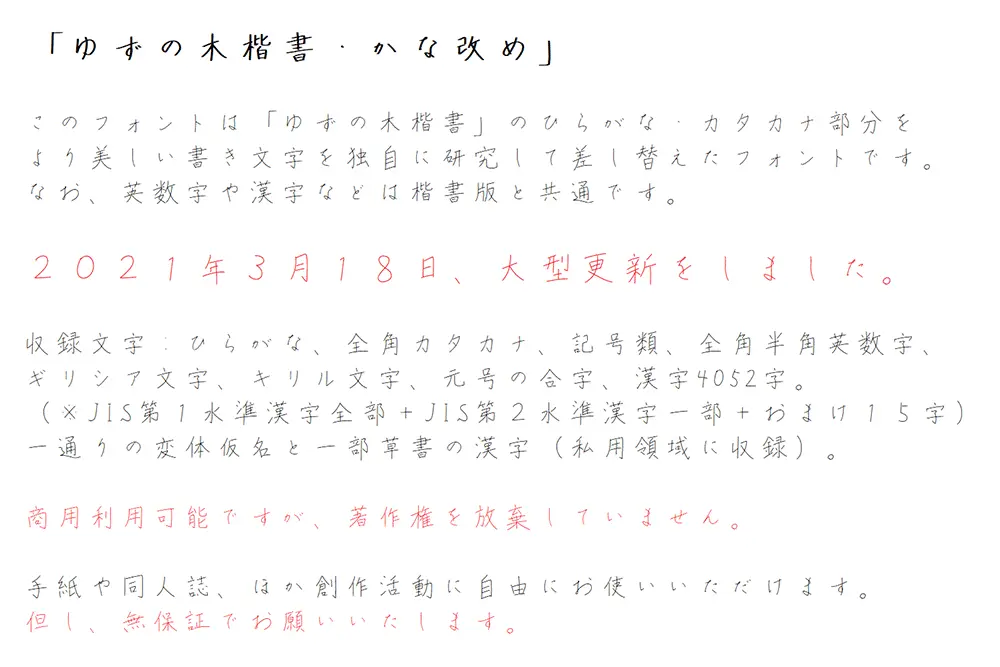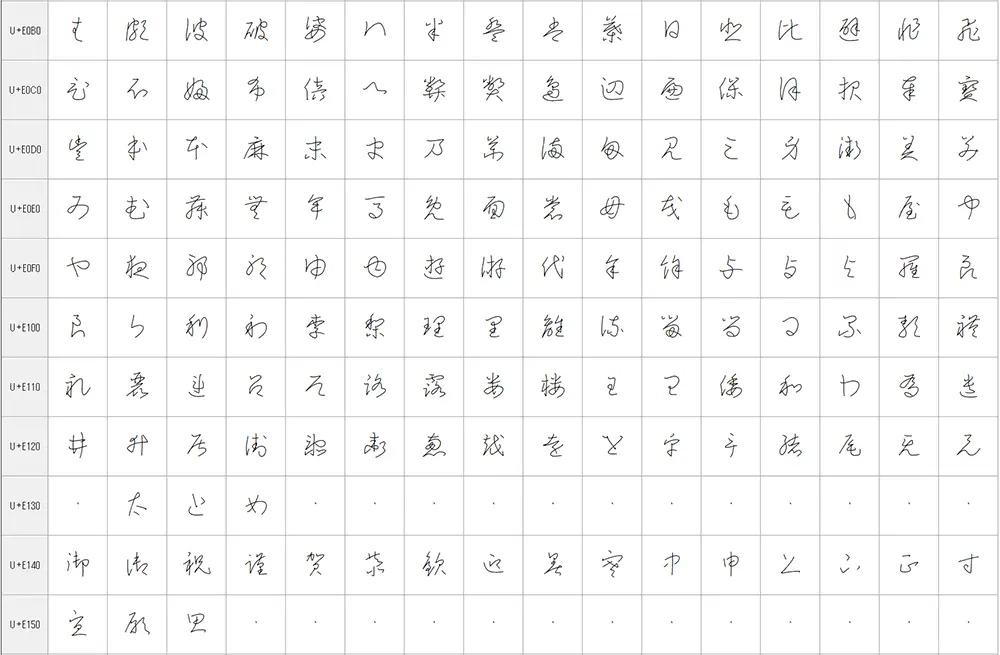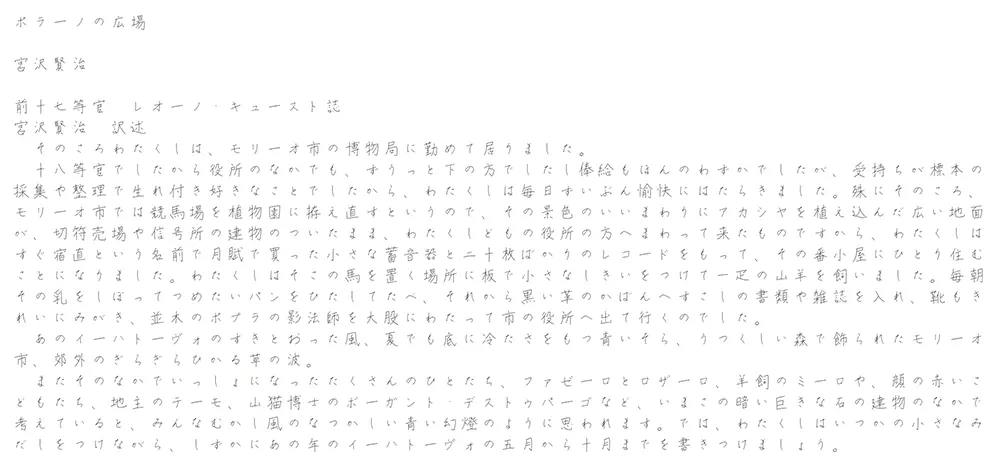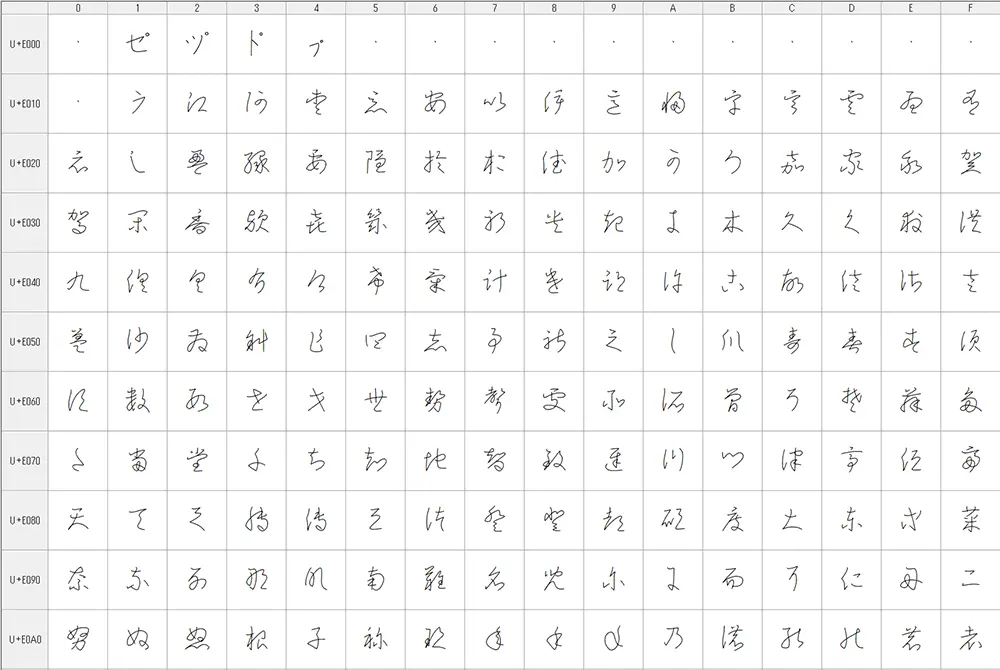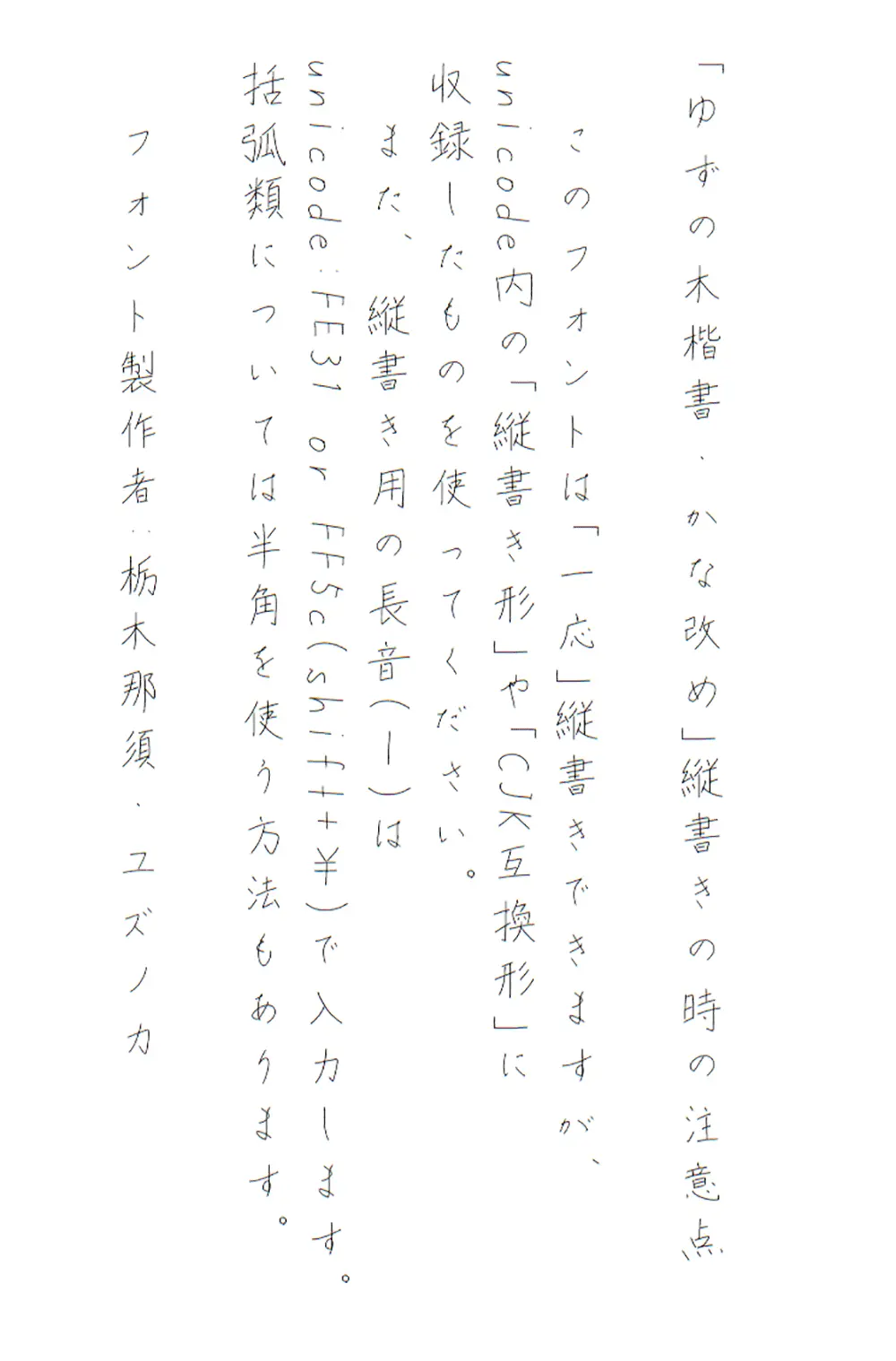
ゆずの木楷書・かな改め是「ゆずの木楷書」的平假名、片假名部分,這是我用我獨立研究的更好的字體替換的字體。另外,在私人領域追加了一套變體假名和一部分草書,可以寫“恭喜”、“新石”、“春風得意”、“恭喜”等。2021年3月18日更新:增加了漢字,與「ゆずの木楷書」通用。
「ゆずの木楷書」のひらがな・カタカナ部分を獨自に研究したより良いものに差し替えたフォントです。おまけで私用領域に一通りの変體仮名と一部草書を追加しました。「御祝」「寸志」「迎春」「お見舞い申し上げます」などが書けます。2021年3月18日更新:漢字を増やしました。(「ゆずの木楷書」と共通です)